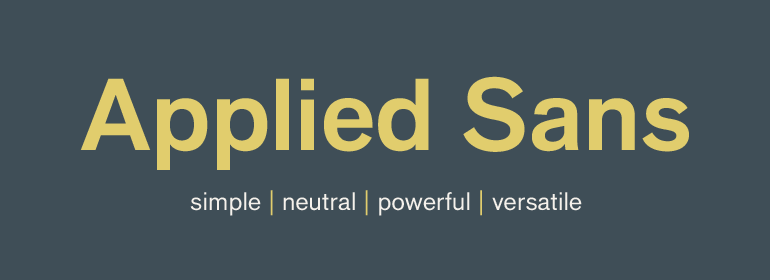
Applied Sans™
Applied Sans™,这款字体结构工整、笔画清晰,兼顾美观与易读性,适用于标题、正文、海报、包装、LOGO 等多种场景。字形优雅稳定,风格百搭耐看,适配日常排版与创意设计,让文字呈现更舒适、更具质感。Applied Sans™一笔一画,皆是细节,以均衡的比例、流畅的线条打造舒适视觉体验,字形端正大气,风格简约现代。无论是商业设计、品牌宣传还是日常排版,都能轻松驾驭,让文字更有格调与力量。Applied Sans™字体下载。
字体品牌: Monotype 设计师:Kobayashi,Akira; Winter,Sandra 字体分类:衬线体 字体属性:外文 字符集:Unicode 发布时间: 2018